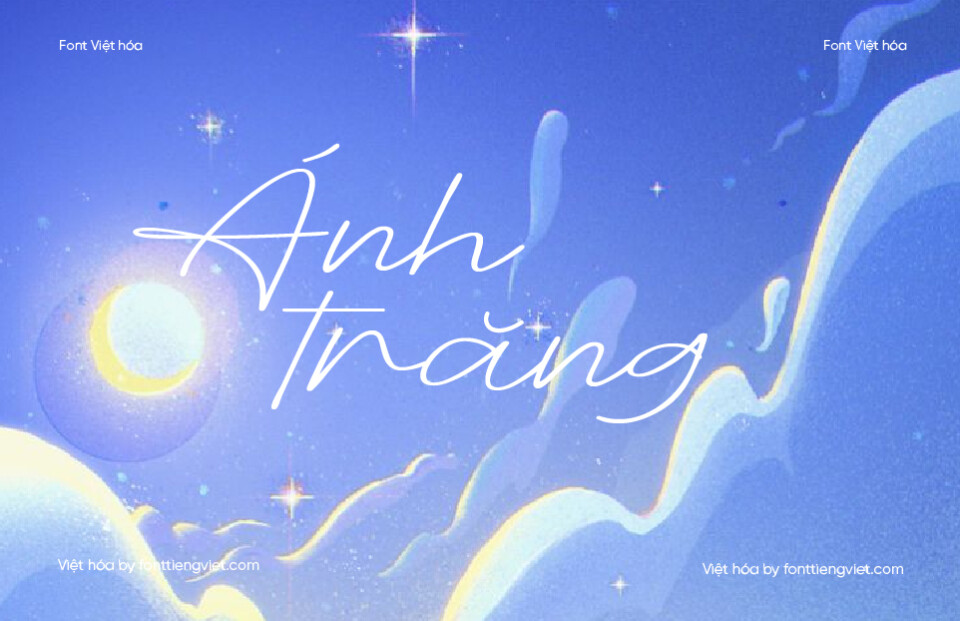
Font Việt hóa 1FTV VIP Winter Prime Monoline – Bộ font thanh lịch cho thiết kế mùa đông
Giới thiệu về Font Việt hóa 1FTV VIP Winter Prime Monoline
Trong thế giới đồ họa hiện đại, việc lựa chọn Font Chữ phù hợp đóng vai trò then chốt tạo nên linh hồn cho tác phẩm. Font Việt hóa 1FTV VIP Winter Prime Monoline là một trong những bộ font viết tay độc đáo nhất hiện nay. Với phong cách monoline đặc trưng, bộ font này mang đến những nét vẽ có độ dày đồng nhất, tạo cảm giác mềm mại và liên tục như dòng chảy tự nhiên của nét bút. Phiên bản Việt hóa này giúp các nhà sáng tạo tại Việt Nam dễ dàng sử dụng trong các phần mềm thiết kế chuyên dụng mà không lo lỗi hiển thị dấu tiếng Việt.
Đặc điểm nổi bật của bộ font monoline cao cấp
Phong cách thiết kế tinh tế và hiện đại
Font Việt hóa 1FTV VIP Winter Prime Monoline nổi bật với cấu trúc mảnh mai nhưng vô cùng chắc chắn. Sự kết hợp giữa nét chữ nghiêng nhẹ nhàng và các đường nối mượt mà tạo nên một tổng thể hài hòa, sang trọng. Đây là lựa chọn lý tưởng cho các dự án yêu cầu tính thẩm mỹ cao như thiết kế thiệp mời, bao bì sản phẩm cao cấp hoặc các ấn phẩm truyền thông mang phong cách tối giản nhưng ấn tượng.
Ứng dụng đa dạng trong giáo dục và đời sống
Với các em học sinh và thầy cô giáo, bộ font này có thể dùng để trang trí slide bài giảng, làm tiêu đề cho các báo tường hoặc thiệp chúc mừng. Tính dễ đọc của Font Việt hóa 1FTV VIP Winter Prime Monoline giúp nội dung truyền tải trở nên gần gũi và ấm áp hơn, đúng như cái tên “Winter” mà nó sở hữu. Độ tương thích cao giúp font hoạt động ổn định trên cả máy tính và thiết kế di động.
Kết luận về trải nghiệm sử dụng font